【座談会】「美酢(ミチョ)」商品パッケージからCMまで、ブランドの世界観を表現するオリジナルフォント135文字の舞台裏
100%果実発酵のお酢から作られた、韓国発のビネガードリンク・美酢。日本でも、健康や美容を意識する人々を中心に人気を集めています。美酢を販売するCJ FOODS JAPANさんは、リブランディングプロジェクトの一環として、美酢のオリジナルフォント制作を企画され、モリサワがそのお手伝いをしました。
今回は、オリジナルフォント完成までの道のりや込めた思いを、同社のお二人と、制作に携わったモリサワメンバーで振り返ります。
1.時代の空気を取り入れたオリジナルフォントでブランドをアップデート
荻野 美酢は日本でも人気が高く、商品や広告を目にする機会も増えました。新商品もたくさん登場していますよね。
池田さん 最初は900mLの希釈タイプのみの展開でしたが、日本の食シーンの多様化に合わせて、2018年からはストレートタイプやゼリー、アルコール商品など、ラインナップを充実させています。お酢飲料というと、従来は「健康のために無理して飲む」イメージでしたよね。美酢は飲みやすく、果実の美味しさを楽しめるのが特徴で、若年層の女性を意識したブランドです。
荻野 そんな美酢のオリジナルフォントを制作したいと、モリサワにお問い合わせいただいたのが、2022年の6月でした。
曺さん 2011年に日本での販売を開始して以来、おかげさまで順調にファンを増やしてきました。ただ、販売開始から時間が経ったこともあり、今の時代に合ったイメージにブランドを再構築して、さらに多くの方々に美酢の持つビューティーベネフィット(便益)を伝えようということになりました。オリジナルフォントの制作はその一環です。
本間 これまでに御社でオリジナルフォントを制作されたことはあるんですか?
曺さん 韓国のCJ FOODSにはコーポレートフォントがあり、歴史あるいくつかのブランドも独自のフォントを持っていますが、日本では初めてです。
荻野 欧文やハングルはトータルの文字数から見て、比較的オリジナルフォントのハードルが低いといえるかもしれませんね。今回はロゴ周りでよく使う漢字、ひらがな、カタカナ合計135文字をオリジナルフォントとして開発したい、というご要望でした。
何万字にも及ぶ日本語の場合、全ての文字をオリジナルフォントで開発するのは時間と費用がかかります。しかし使用頻度の高い文字をピックアップするのは、短納期かつ低コストで制作できる良いアイデアだったと思います。
2.象徴性・視認性・汎用性。オリジナルフォントの3要件
本間 オリジナルフォントを開発される前は、既存フォントを使われていたんですよね。
曺さん はい。以前のロゴは、既存のフォントをベースに作ったもので、優しく自然な雰囲気が美酢のブランドイメージともとても合っていると感じていました。モリサワさんはどんな雰囲気のフォントも得意とされている印象があり、今の美酢、さらには10年後の美酢のイメージも的確に表現してくださると感じて、お願いしました。
荻野 ありがとうございます!フォント開発にあたって、言語化しづらいイメージをお客様と共有することは重要でありながら難しい部分でもあるのですが、お伝えいただいた要件が非常にクリアでしたので、制作の流れもスムーズだった印象があります。
曺さん そうですね。オリジナルフォントを作るにあたり、まず「守っていくもの」と「変えるもの」を明確にすることが重要だと考えました。美酢の優しくカジュアルな世界観は守りつつ、そこに現代的なフレッシュさや活気を加えていく、またロゴや商品パッケージだけでなく、映像、ウェブ、オフラインの販促物にまで幅広く使用するものなので、どの媒体であっても美しく表現できる汎用性も不可欠でした。それだけに、制作時に考慮すべきことは多かったですね。
荻野 具体的にはどういった部分ですか?
曺さん 同じ広告でも、テレビと屋外のデジタルサイネージでは、対象物を見る距離がまったく違いますよね。また、紙に印刷することもあればモニターに表示するケースもあります。媒体や大きさを問わず、お客様がきちんと読めて、かつ美酢の世界観が伝わるようにするには、あらゆる角度から慎重に検討する必要がありました。
ただ、モリサワさんがフォントデザイン案だけでなく、実際の商品に展開した場合どう見えるか、サンプル画像を作成してくださったので、視覚的なイメージがつかみやすかったです。
本間 「きちんと読める」こと、カタカナの視認性の高さは重要なポイントでしたね。
曺さん 大事ですね。美酢のロゴにはカタカナで「ミチョ」と読み仮名を入れるんですが、常に大きく入れられるわけではありませんし、印刷方法によっても見え方は変わります。フレーバー名もカタカナが多く、ロゴの下に小さく入るケースが多いんですよね。
本間 下に色を引くとさらに読みづらくなりますしね。なので、実際に商品を購入して研究しました。文字がプリントされたキャップのふたを見ながら、小さくても印刷でつぶれないよう、文字のパーツを離して空間を持たせようとか、印刷に耐え得る文字の太さはどれくらいか、といったことを考えて提案しました。
荻野 それだけではなく本間は、既存フォントと組み合わせて使う汎用性も意識していたように思います。
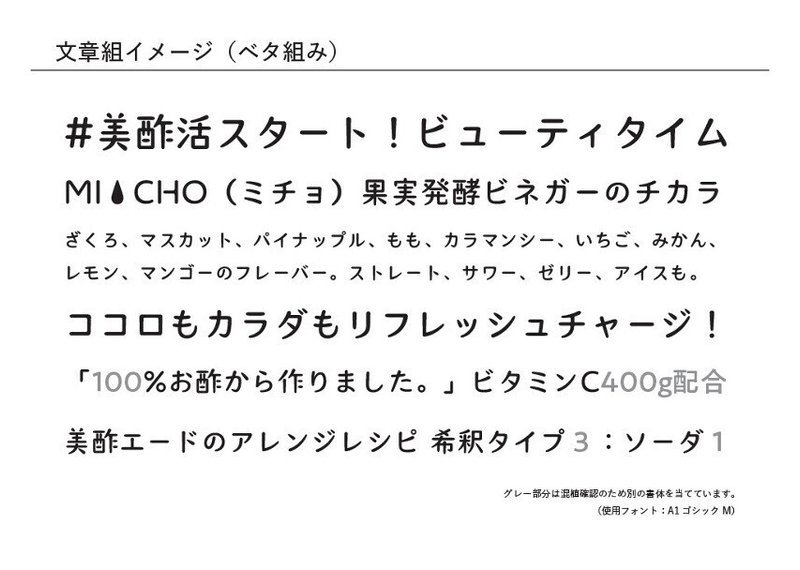
本間 そうですね。文字数を絞り込んでのご依頼だったので、最初から他フォントとの併用を想定していました。なので、他フォントと文字サイズが大きく変わらないよう、ちょうどいい塩梅を探りました。
最初に、キュートでアクティブな印象を持たせた案、直線的な要素を強めて爽やかな印象を持たせた案など4つのイメージパターンでデザインを作成しました。漢字はブランドイメージを保つ意図もあって、既存の美酢のロゴから大きく変えず、少しずつ印象を変えたものから全く変えないものまで提案に加えました。カタカナとひらがなは漢字とのバランスをみながら、それぞれのイメージに合わせてデザインし、提案しました。
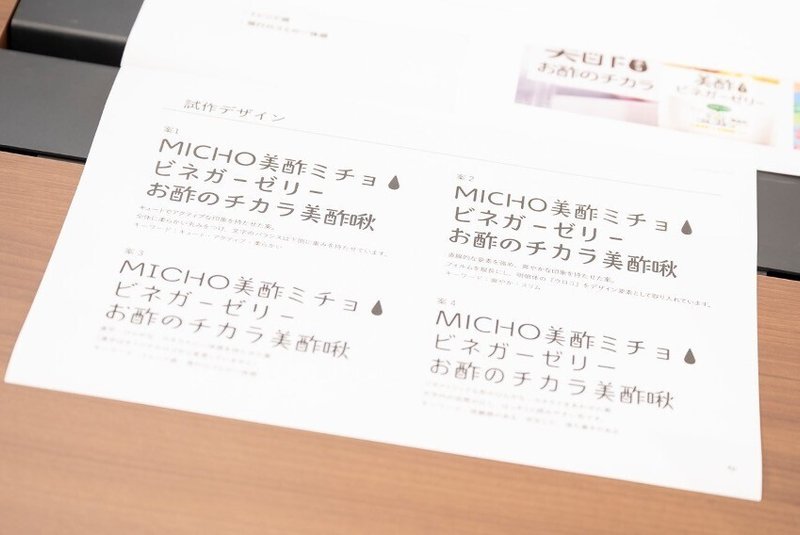
曺さん お願いした通りの雰囲気で、さらに細かくパターンを分けてくださったので、新しい美酢のイメージによりフィットしたものを選ぶことができました。文字自体の完成度も高く、パッケージでも販促物でも読みやすく入れられるなと思いました。
本間 最終的には全体に丸みを持たせ、重心を低めにとってかわいらしさを出し、アクティブ性を高めたパターンに決定されましたね。その理由をうかがってもいいですか…?
曺さん 「ブランドイメージと合うか」という象徴性の部分と、視認性、汎用性。一番大切なこの3点をクリアしていたのはもちろんですが、デザイナーとしてとても魅力を感じました。理屈で選ぶところと感性で選ぶところがピタっと一致しましたね。
本間 わっ、ただただ嬉しいです!
曺さん 文字の太さに関しては、ワンウエイト(1種類の太さ)でありながらもさまざまな媒体で使えるようにお願いしましたが、複数のパターンを見せてくださったので、最適な太さを選ぶことができました。
本間 ご提案したものに対して、もう少し太くしたいというご要望をいただき、文字全体の太さを変えた2パターンと、先端やはらいの太さは変えず、他の部分の太さだけを変えた2パターン、計4パターンをご提案しました。
曺さん 先端やはらいの部分をそのままにしていただいたパターンでは、もともとのアクティブなイメージをそのままに、太さを維持できて希望通りでした。本当にわずかな違いではあるんですけれど、見た目や雰囲気が大きく変わることがよく分かりました。
3.オリジナルの記号も! カスタムフォントでできること
荻野 今後、多くの場面で使用していただくフォントですので、デザインチームのみなさんの使いやすさに寄り添って、タイプデザイナーとしてとことんこだわりましたよね。
本間 カタカナの「タ」の点の打ち方でしょうか。当初上付きだったんですけど、曺さんから「下にできませんか」とご連絡をいただいて。
曺さん そうそう。デザインチームのメンバーから「下に点がある方が見慣れた感じがする」と意見が出まして。いろんなフォントの「タ」を検証して、デザイン以外の部署の人にも見てもらい、最終的に変更をお願いしました。フレッシュさも必要ですけど、安心感も大事ですから。
あとは音引きの長さも細かく調整しましたね。フレーバー名には「グレープフルーツ」など複数の音引きが入るものが多く、そのままだと音引きだけが目立ってしまう。よって当初は「音引きは短めで」、とお願いしていました。
本間 短めの音引きをデザインし、実際に文字を並べたときに、もう少し長めがいいんじゃないかとコメントをいただいて。それで、キーボード変換で呼び出す形で、長めと短めの2種類の音引きをご用意しました。文字を詰めて表示する商品パッケージには短い音引き、それ以外は長い音引きと使い分けができるようになっています。
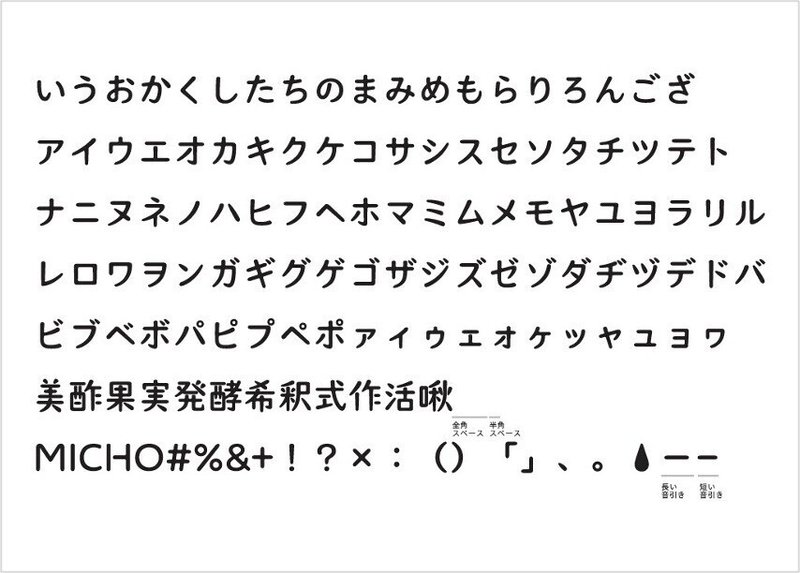
曺さん 長体(文字の横幅を縮めること)をかけることもできるんですが、そうやって無理やり短くするより、最初からデザインされたものを使えば一番きれいに見えるだろうと。
本間 今回、初めてトライしたのが「しずく」マークの制作でした。制作文字として作ってほしいとのご要望を受けて、ひらがなの「しずく」を漢字に変換(雫)するとこのマークが出るように設計しています。
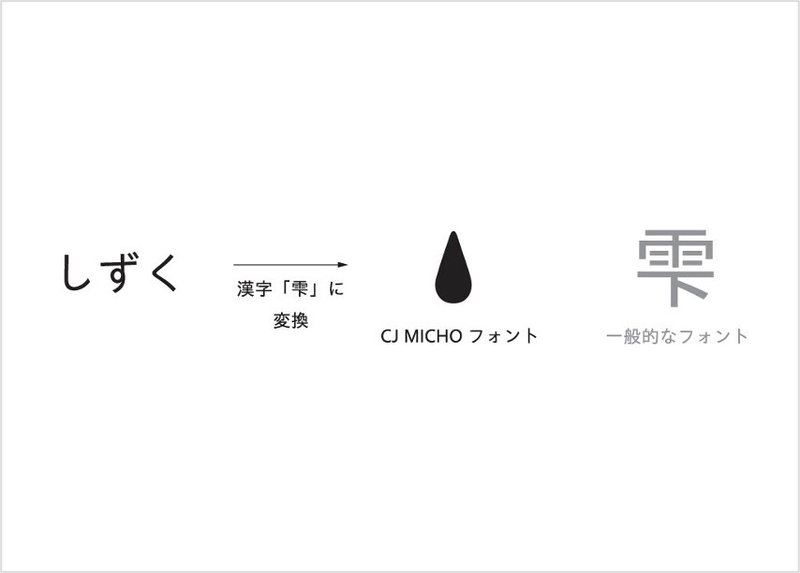
曺さん 記号のひとつとして作っていただいた、美酢だけのマークです!
荻野 文字として扱えるので、級数で大きさや色を自由に変えられます。そこは弊社が提供する、カスタムフォントならではのメリットといえますね。文字の呼び出し方も、お客様が使いやすい形にアレンジできますので、どんどん活用していただきたいです!
4. 「ミチョフォント」が広げるブランドの世界観
荻野 既にCMで新フォント「CJ MICHO」が採用されていますが、実際の制作物に使ってみてどのように感じましたか。
池田さん 社内では通称「ミチョフォント」と呼んでいます。他のフォントと併用する形ではありましたが、違和感なくマッチしていたのでよかったです。とはいえ今後、さまざまな媒体で大々的に活用していく上で、文字数を追加する必要も出てくるのかな、と思っています。
■動画「#美酢活 で美ルーティーン」篇
曺さん 一つの文章内では、できる限り他フォントを混ぜずにミチョフォントで統一したいですね。
池田さん 私は制作の実務には関わっていないのですが、ミチョフォントが完成したことによって、デザインの可能性がものすごく広がったと感じていて、これからが楽しみです。このプロジェクトに関わったメンバー全員、作ってよかった!と思っていますね。
曺さん 文字を打つだけですぐに美酢の世界観を広げられるところは非常に助かっています。本格的な活用はこれからですが、フォント自体は使いやすく、今後、パッケージやさまざまなデザインがスムーズに行えそうです。また、美酢がここまで成長して、ブランド固有のフォントを持てたことにプライドを感じます。そしてそれをモリサワさんに作っていただいたのは、個人的にもとてもうれしいことでした。
本間 自分が携わったミチョフォントを、今後、街やお店で目にしたり、購入したりできるんだなと思うと、私もすごく楽しみです!
荻野 パッケージや各種販促物など幅広いシーンでご利用されるということで、可読性を重視しながらも、世界観を表現する、というご依頼に合ったフォントをご提供できたのではと思います。ミチョフォントがさまざまな場所で活躍されれば、フォントメーカーとしてもこれほどうれしいことはありません。本日はどうもありがとうございました!
オリジナルフォント開発という一つの目標に向かって、思いを共有しながら進んだ、各人の熱量が感じられる座談会でした。みなさんがどこかで「ミチョフォント」を目にされた際に、今回ご紹介したポイントを思い出していただけるとうれしいです。